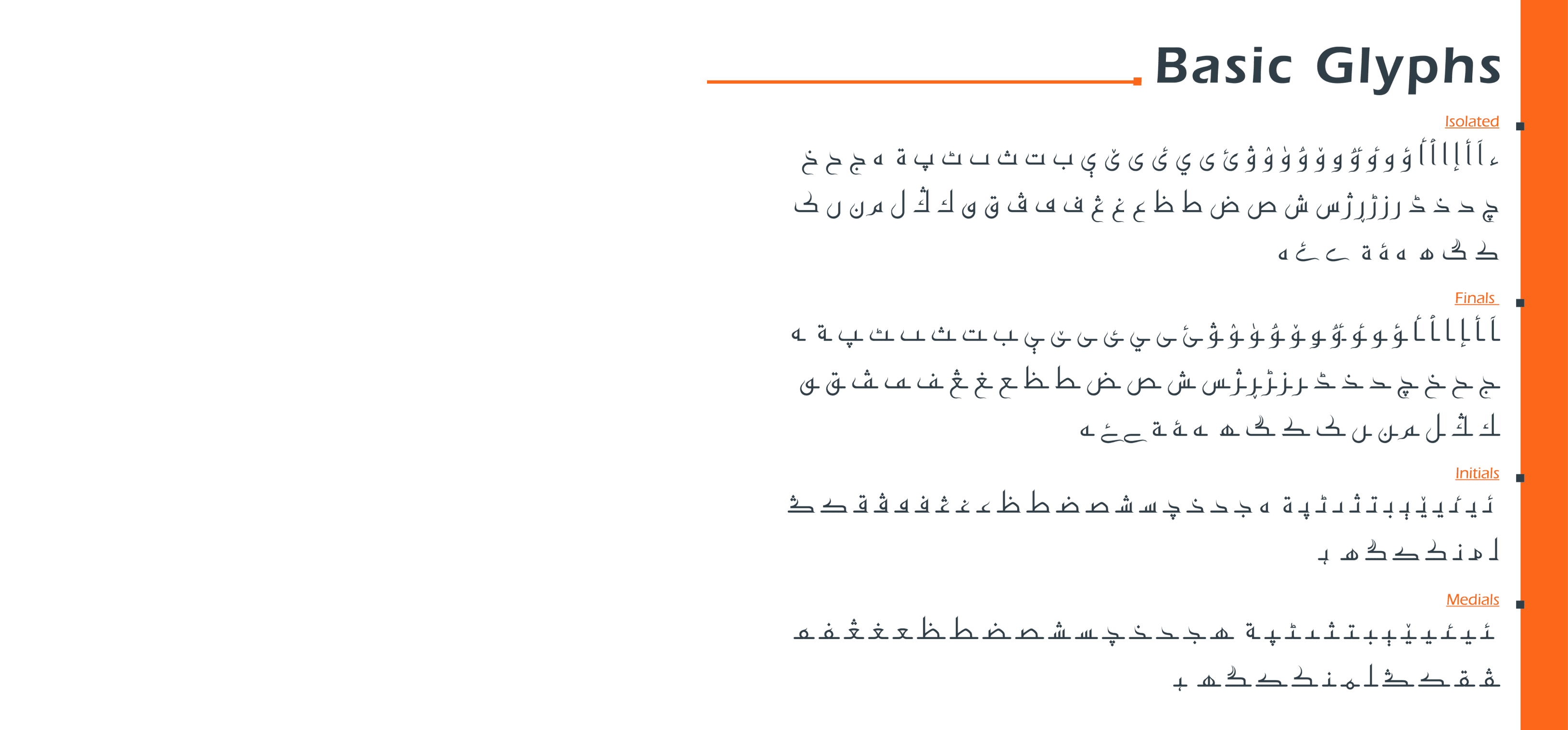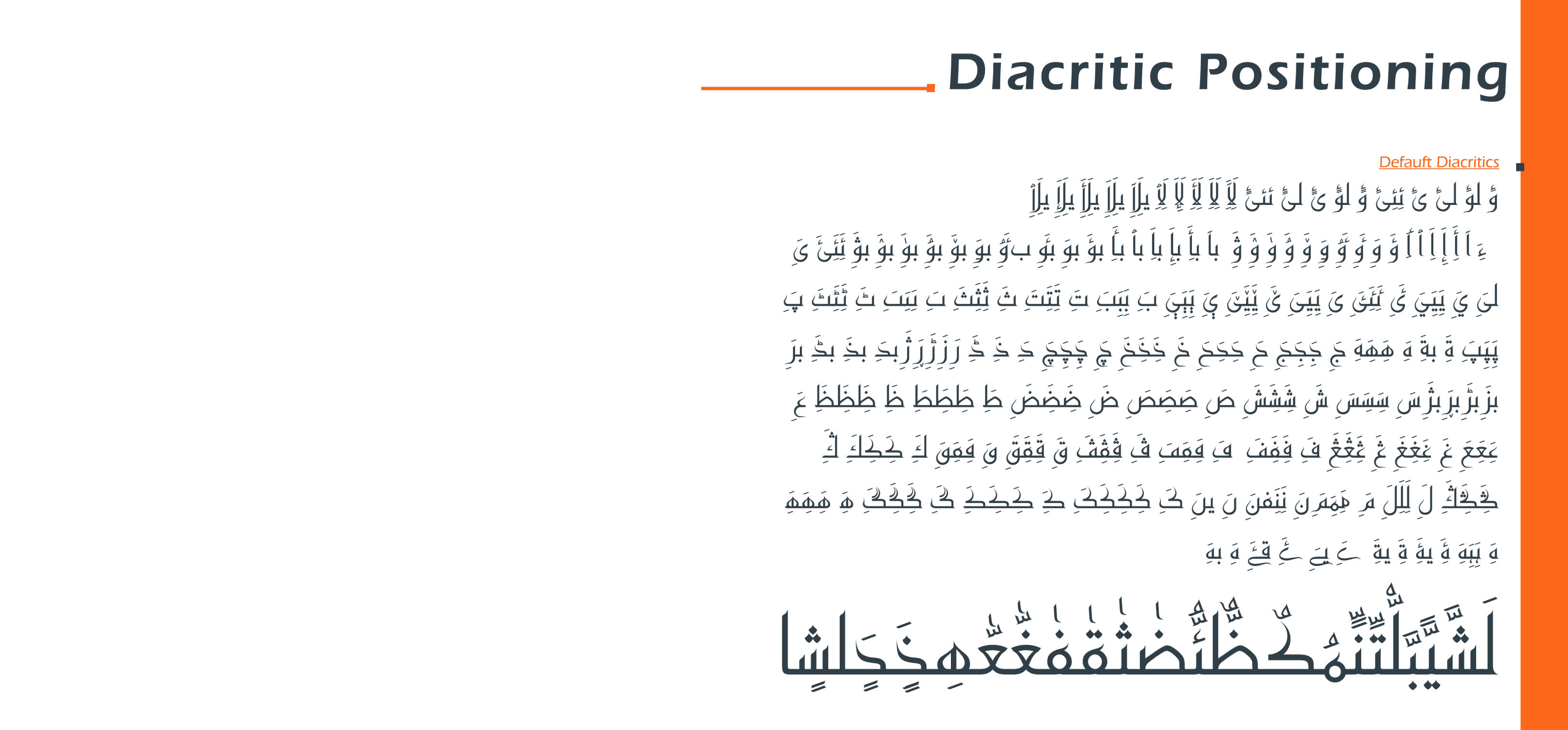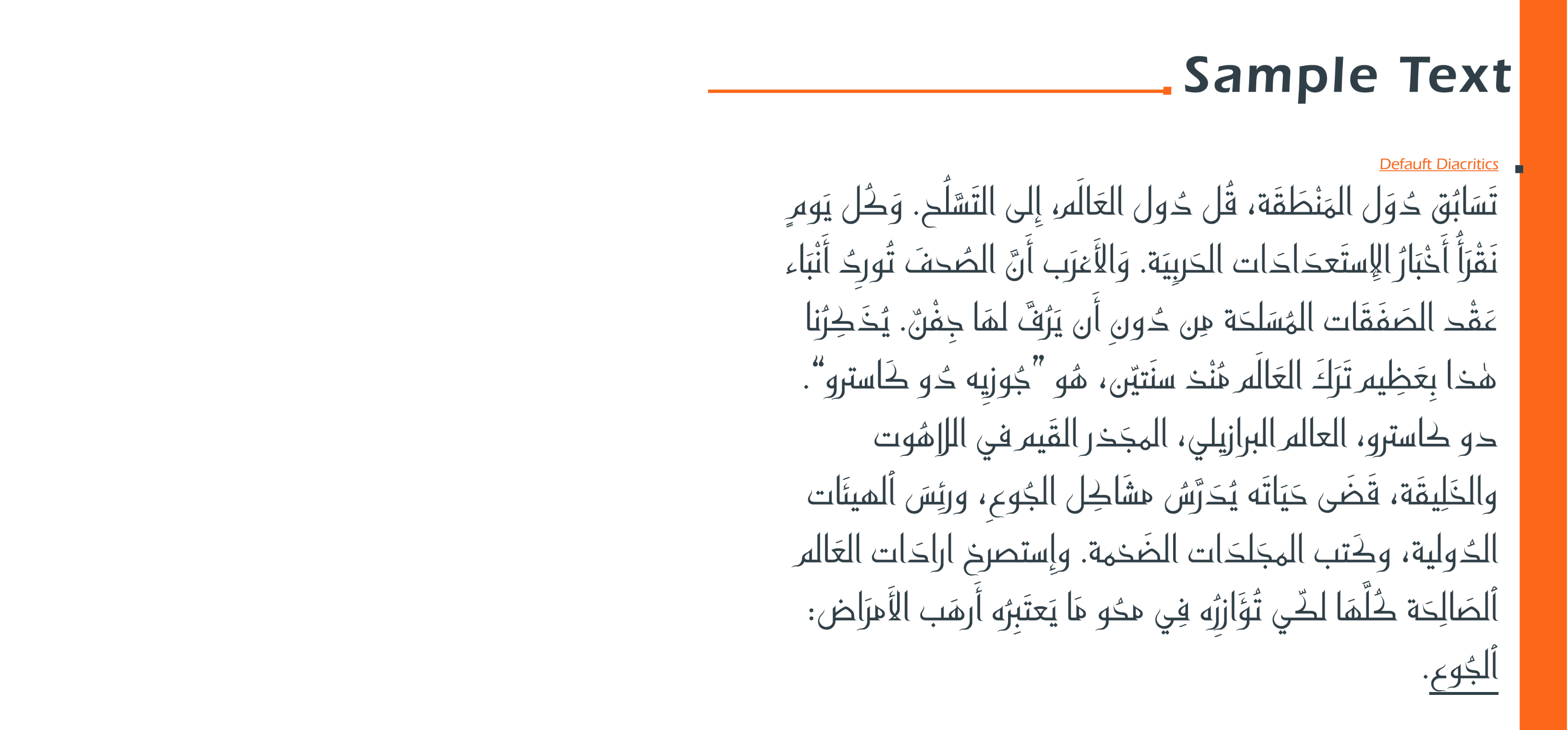
الخط JH Fares هو خط عصري وبسيط بأسلوب كوفي.
يلاحظ المستخدم وجود فراغات بيضاء واسعة حول النص، مما يجعل الخط عالي الوضوح وسهل القراءة.
يُعد الخط الكوفي من أقدم الخطوط العربية، وقد ظهر لأول مرة في مدينة الكوفة بالعراق. وقد اشتُق الخط الكوفي الأصلي من الحروف الآرامية، ثم خضع لاحقًا للعديد من التحسينات.
الاستخدامات النموذجية لهذا الخط تشمل: الكتابات الزخرفية للمساجد والقصور، عناوين المجلات والصحف والكتب، وبطاقات التهنئة.
الخط JH Fares هو خط عصري وبسيط بأسلوب كوفي.
يلاحظ المستخدم وجود فراغات بيضاء واسعة حول النص، مما يجعل الخط عالي الوضوح وسهل القراءة.
يُعد الخط الكوفي من أقدم الخطوط العربية، وقد ظهر لأول مرة في مدينة الكوفة بالعراق. وقد اشتُق الخط الكوفي الأصلي من الحروف الآرامية، ثم خضع لاحقًا للعديد من التحسينات.
الاستخدامات النموذجية لهذا الخط تشمل: الكتابات الزخرفية للمساجد والقصور، عناوين المجلات والصحف والكتب، وبطاقات التهنئة.
الخط JH Fares هو خط عصري وبسيط بأسلوب كوفي.
يلاحظ المستخدم وجود فراغات بيضاء واسعة حول النص، مما يجعل الخط عالي الوضوح وسهل القراءة.
يُعد الخط الكوفي من أقدم الخطوط العربية، وقد ظهر لأول مرة في مدينة الكوفة بالعراق. وقد اشتُق الخط الكوفي الأصلي من الحروف الآرامية، ثم خضع لاحقًا للعديد من التحسينات.
الاستخدامات النموذجية لهذا الخط تشمل: الكتابات الزخرفية للمساجد والقصور، عناوين المجلات والصحف والكتب، وبطاقات التهنئة.